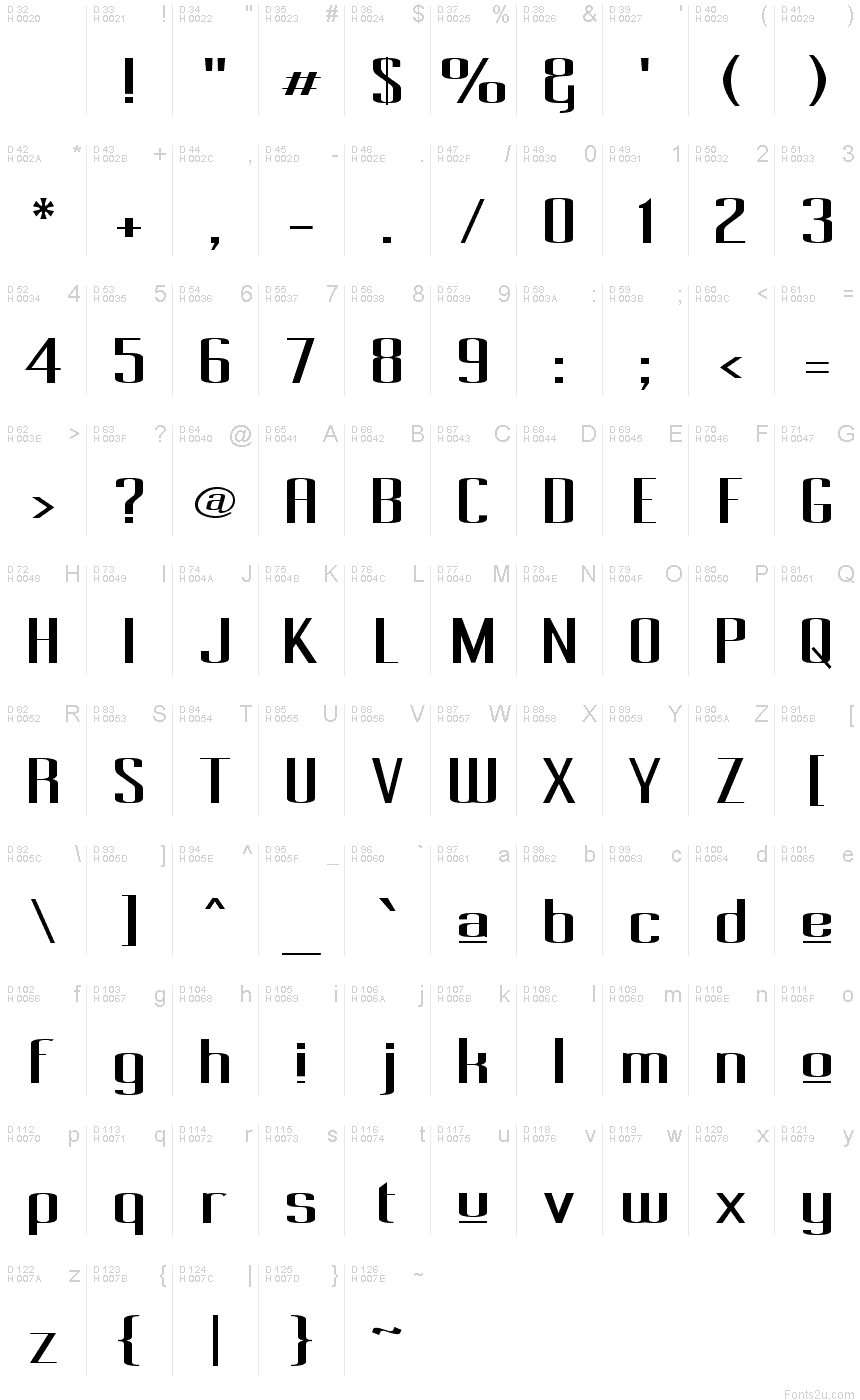
Pecot Upper autorstwa Grahama Meade’a to darmowy, utrzymany w stylu retro font typu display, wyróżniający się zaokrąglonymi, geometrycznymi kształtami i wyrazistym poziomym rytmem. Litery zachowują proste i pionowe formy, łącząc łagodne krzywizny, kwadratowe krawędzie i precyzyjne wycięcia, co nadaje projektowi starannie wykończony, mid-century charakter.
Pecot Upper świetnie sprawdza się w tytułach plakatów, logotypach, okładkach magazynów, opakowaniach i oznakowaniach, które wymagają stylizowanego, ale powściągliwego wyrazu. Ten darmowy krój pisma dodaje charakteru krótkim nagłówkom, brandingowi, grafikom eventowym i akcentom redakcyjnym, nie przytłaczając przy tym układu.